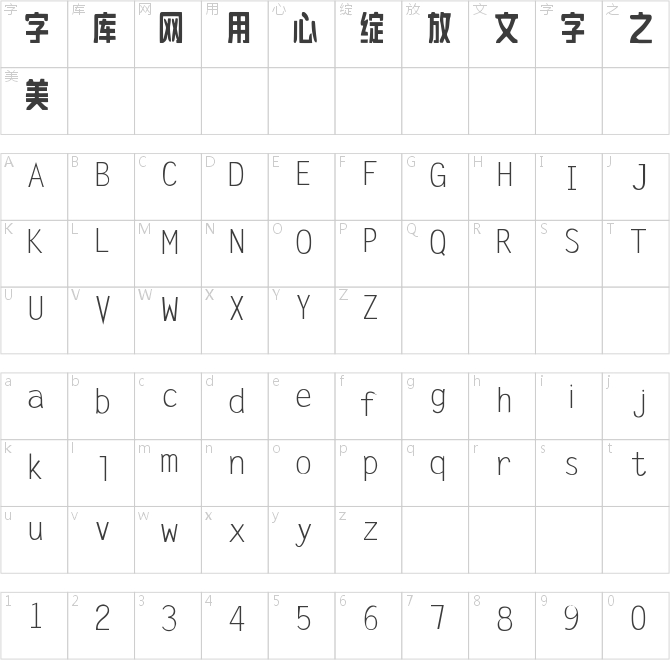
字体家AI造字前进
这是一款由字体家AI造字出品的一款字体,字体风格端正而富有年代感,类似民国时期的那种大字报字体,故取名前进。
字体家AI造字前进字体字库是一款让人赏心悦目、百看不厌的中文字体,适合各类广告和产品包装设计应用,字体大小3.47MB,格式为ttf字体,上传用户是細雪無聲,作者/版权方为字体家